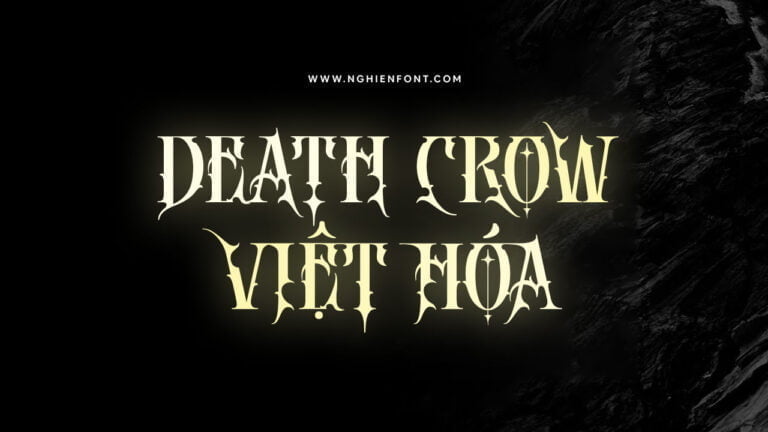
Font việt hóa BHN DEATH CROW – Kiểu font Gothic
Font viet hoa DEATH CROW
DEATH CROW Font mang phong cách Gothic metal cho phép bạn sử dụng phông chữ này để nâng cao tác phẩm nghệ thuật của mình, phông chữ này phù hợp để hoàn thiện các thiết kế minh họa, logo, poser, bìa truyện, v.v.
Tính năng
• Uppercase
• Lowercase
• Numeral
• Functional
• Multilingual
• Uppercase Alternate 1
• Uppercase Alternate 2
DEATH CROW với các nét chữ vô cùng ấn tượng mang đến cảm giác cổ điển và một cái gì đó ma mị, bí ẩn phù hợp sử dụng để làm tiêu đề nó sẽ hiển thị tốt khi sử dụng ở kích thước lớn.
Hỗ trợ đa ngôn ngữ và tính năng OpenType vì vậy bạn có thể tha hồ sáng tạo để tạo ra những tác phẩm thiết kế ấn tượng và hoàn hảo hơn.